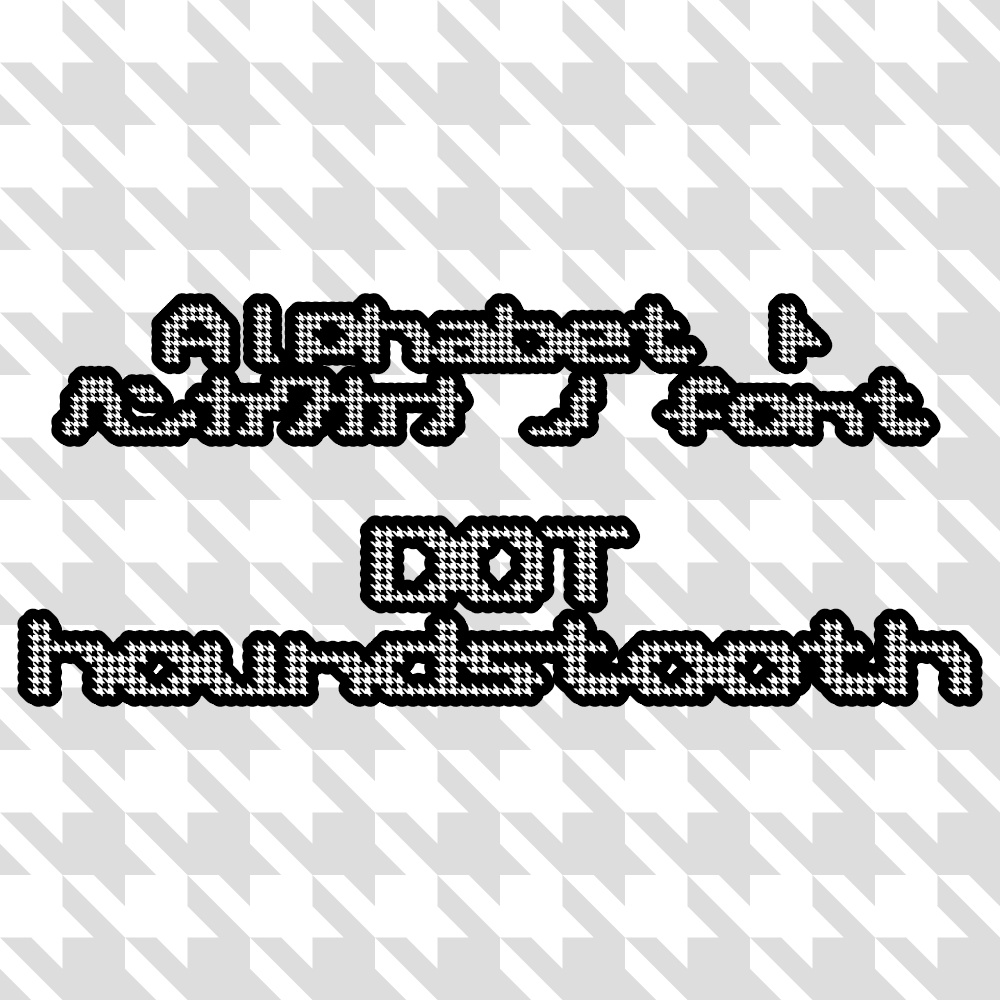
torisippoフォント DOThoundstooth ドットハウンドトゥース(ドット千鳥格子)Digital0 JPY免費下載DOThoundstooth_v1.0a.zip (29.4 KB)DOThoundstooth_v1.0a.zipAbout Gift千鳥格子をドット化してフォントを作りました。 このフォントはドットジグソーのスプリクトにて作成されています。 興味のある方は以下を参照してください。 https://torisippo.booth.pm/items/7882952フォントデータ形式TrueType(.ttf) OpenType(.otf)更新履歴2026/05/08 v1.0a 標準/太字フォントを梱包 2026/04/12 v1.0 初版torisippoVisit FANBOX!Fontsフォント Auxiliary line オーグジュアリラインtorisippo0 JPYFontsフォント でんでんえん/でんえんえんtorisippo1,200 JPYFontsフォント ひらすわぷろtorisippo800 JPYFontsフォント PCB10 プリント基板配線パターンフォントtorisippo0 JPYFontsフォント MahjongMPSZColortorisippo0 JPYFontsフォント DOTjigsaw (fontforge用フォント生成スプリクト付き)torisippo0 JPYSoftwareFormat Renamer ~キーボードを極力使わないリネームソフト~torisippo1,000 JPYFontsフォント マステ丸 ラウンド25torisippo0 JPYFontsフォント ひらすわtorisippo0 JPYFontsフォント メニーワンtorisippo0 JPYFontsフォント MahjongZSPMtorisippo0 JPYFontsフォント MahjongMPSZtorisippo0 JPYFontsフォント ブルーテイルtorisippo0 JPYFontsフォント デンエンtorisippo0 JPYFontsフォント カールtorisippo0 JPYFontsフォント ウォータービーズtorisippo0 JPYFontsフォント ウーファーtorisippo0 JPYFontsフォント ラバーボールtorisippo0 JPYFontsフォント フォースフルドットtorisippo0 JPYFontsフォント エキゾチシズムtorisippo0 JPY查看更多